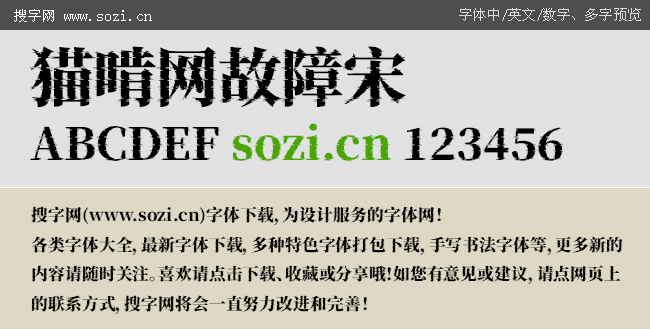
貓啃網(wǎng)故障宋
搜字網(wǎng)給大家提供一款貓啃網(wǎng)故障宋中文字體下載,貓啃網(wǎng)故障宋是一款藝術(shù)宋體字體,字體基于思源宋體CN改造,所以繼承了思源字體字?jǐn)?shù)滿(mǎn)的優(yōu)點(diǎn),用起來(lái)不用擔(dān)心缺字少字。支持免費(fèi)商用。適合應(yīng)用于藝術(shù)設(shè)計(jì)、平面宣傳設(shè)計(jì)、網(wǎng)頁(yè)設(shè)計(jì)、海報(bào)設(shè)計(jì)等應(yīng)用。